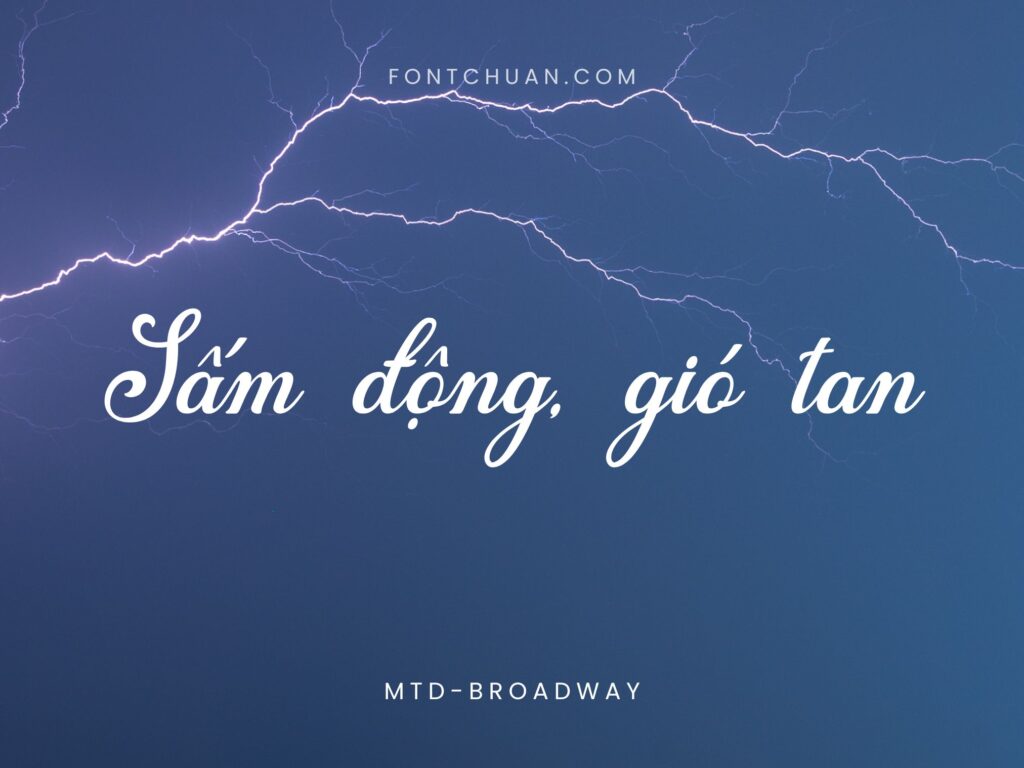
Font MTD Broadway Việt Hóa
Font MTD Broadway Script là một kiểu chữ viết tay được thiết kế với phong cách brush, mang đến vẻ đẹp tự nhiên và năng động. Font này hỗ trợ đa ngôn ngữ, bao gồm cả tiếng Việt, mở rộng khả năng ứng dụng trong các thiết kế đa dạng. Đây là một trong những phông chữ được cộng đồng thiết kế đánh giá cao và sử dụng trong nhiều dự án sáng tạo, đáp ứng nhu cầu đa dạng của người dùng.
MTD Broadway Script nổi bật với các đường nét mềm mại và uyển chuyển, tạo cảm giác thân thiện và gần gũi. Font rất phù hợp cho các thiết kế áo thun, tạp chí, bìa điện thoại, mạng xã hội, menu nhà hàng, thiệp mời và nhiều ấn phẩm khác đòi hỏi sự sáng tạo và cá nhân hóa. Các ngành nghề phù hợp bao gồm quảng cáo, giáo dục, công nghệ, thiệp cưới và ảnh cưới. Font này cũng lý tưởng cho các sự kiện như Tết, Giáng sinh, Valentine và các lễ hội khác.